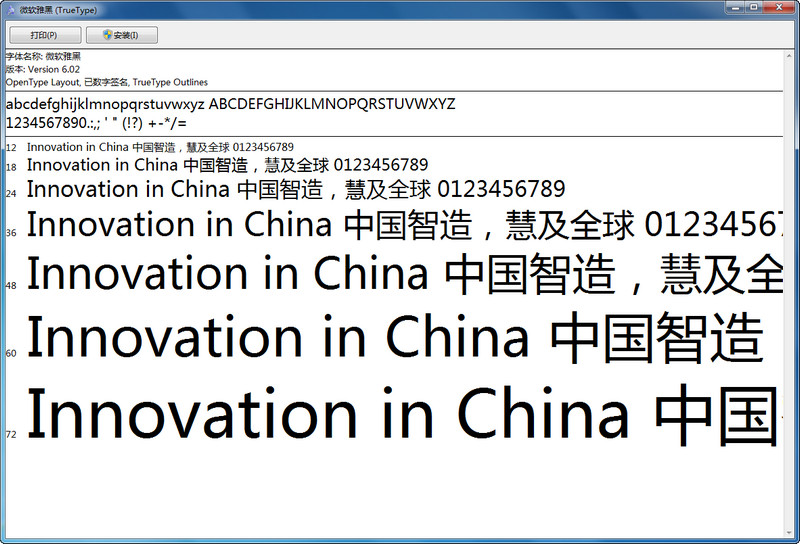
微軟雅黑是美國(guó)微軟公司委托中國(guó)北大方正電子有限公司設(shè)計(jì)的一款全面支持ClearType技術(shù)的字體。Monotype公司負(fù)責(zé)字體Hinting工作。它屬于OpenType類(lèi)型,文件名是MSYH.TTF,字體設(shè)計(jì)上屬于無(wú)襯線(xiàn)字體和黑體。
1. 更優(yōu)美而現(xiàn)代的字形設(shè)計(jì)。
2. 單獨(dú)設(shè)計(jì)的粗體。
3. 更清晰的小號(hào)字顯示。
3. 顯示品質(zhì)優(yōu)異的斜體。